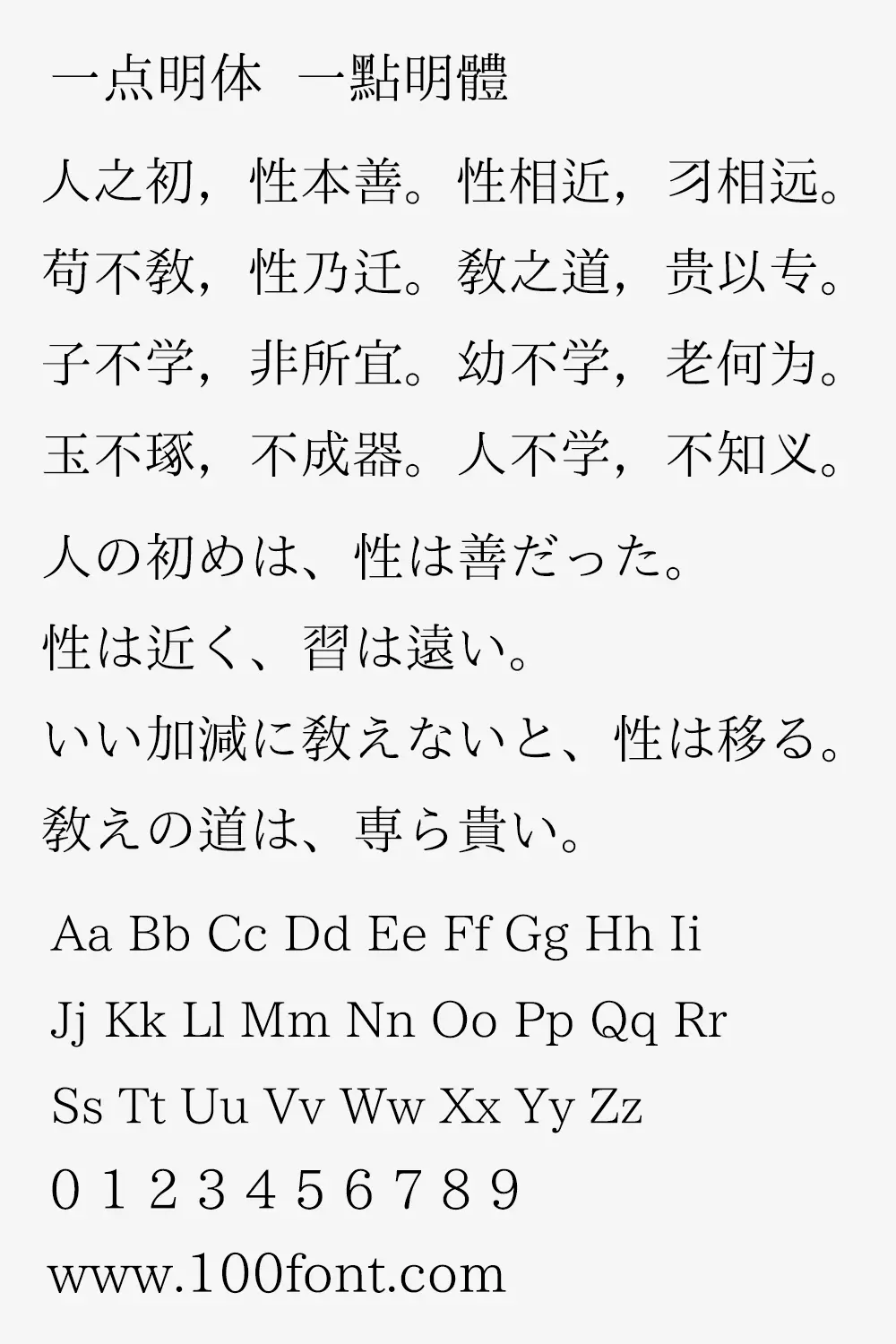
I.Ming ((I.明體 / 一點明體 / 一點明朝 / 一點明體 )乃系一套依照傳承字形標準化文件《傳承字形部件檢校表》的推薦字形標準,並以TrueType格式封裝、依照Unicode編碼的OpenType字體。
我們希望「I.明體」可以作為實際示範,讓大家明白製作字體時,可以採用依照傳承字形標準化文件推薦字形,同時仍然依照Unicode編碼、符合OpenType技術,並期待各字體廠商、字體制作者都能仿效,推出更多開源或商業市場上的傳承字形字體,以收拋磚引玉之效。
「I.明體」這字體名稱裡的「I」是羅馬數字「一」,「I.」唸作「一點([粵]Jat1 dim2、[中古]Qjit temx、[客]Jit7 diam3、[北]Yī diǎn、[日]いちてん、[英]One-dot)」,象徵筆畫的基本:點與線。
信念
漢字,在當今語文中,地位無可取代。它是唯一廣泛通行的意音文字(logogram),每個構字有其字理依據,可上追字源,追蹤每個漢字背後的故事。由龜甲獸骨、鐘鼎禮器上圖形味甚重的漢字,發展至今天,漢字展現了多變的外貌。
現在,進入了信息爆炸的社會,漢字仍不失其生命力。今天大家使用的漢字,主要有兩大類:一是手寫體,由前人的楷書、行書書法演變而來,講求靈活的變化,展示執筆者的修為,營造行間的氣韻;二是印刷體,亦活躍於各種電子屏幕,上宗中國蓬勃且領先全球的印刷術裡,所使用的雕版及活字造形,講求其清晰、理性,結構穩重而明目,筆畫井然且有理。
按類別不同,兩種字在筆畫表現上,一向有所差異。手寫求活,有些筆畫趨於書寫時的便易;印刷求精,筆畫大多保留傳統理性。因此,印刷體的傳承文字,本以致力保留字理為正道。
「I.明體」依照傳承字形標準化文件《傳承字形部件檢校表》的推薦字形標準制作,力求遵從字理,展現傳承漢字構字的科學系統。同時,我們另備「I.明體異體」,呈現傳統印版字中常見的異體。
「一點明體」(I.Ming):收錄力求遵從字理的傳承字形。
「一點明體CP」(I.MingCP):與「一點明體」一樣,唯全形標點置中。
「一點明體異體」(I.MingVar):部份漢字改為收錄一些也常見,但字理上未必比上者佔優的傳承字形。
「一點明體異體CP」(I.MingVarCP):與「一點明體異體」一樣,唯全形標點置中。
「新一細明體」(PMingI.U):與「一點明體CP」一樣,唯行高修改至跟Windows系統細明體相同。
「新一細明體異體」(PMingI.UVar):與「一點明體異體CP」一樣,唯行高修改至跟Windows系統細明體相同。
歷史
「I.明體」經過許多人的努力才誕生。其前身是「IPA字體」。
2009年,日本「IPA」以符合「開放原始碼促進會(Open Source Initiative)」開源定義的「IPA開放字體授權協議」,發佈兩款「IPA字體」,分別為「IPA明體(IPA明朝)」及「IPA黑體(IPAゴシック)」。字體衍生自林隆男(Takao Hayashi)所設計的兩款字形:TypeBank公司的「TB明體」和「TB黑體」。字體包含了日本常用的字元,以供日本人使用。
後來,經過多年的持續修補及修訂,「IPA明體」擴充成「IPAex明體」、「IPAmj明體」。在「IPAmj明體」裡,正體漢字部份已補完得頗齊全,只是仍有少數常用字缺字。預設顯示的寫法仍以日文為主,字體同時收錄了許多異體寫法,惟須採用特定程式方能顯示。其2013年11月的版本,收錄了CJK基本漢字18072個,擴展A漢字5765個,擴展B漢字25320個,擴展C漢字380個,擴展D漢字108個,未映像的異體等漢字9065個。
2013年底,Halasjack公開釋出「IPA明體補字」,在「IPAmj明體」的基礎上,修改了部份日文寫法為中文寫法,把異體字裡符合中文原體寫法,改為預設顯示的字元。他又用正體字替代缺少的簡體字。當中「一簡對多正」的字,如「發」、「歷」等,Halasjack增補了字元,不用某個正體字代替,以免出現別字。此外,Halasjack又自造了百餘個GB2312的缺字,使字體能夠完全顯示GB2312漢字,雖然部份簡體字顯示作正體字,但已能滿足大陸使用者的一般需要。字體並含有部份A區和B區漢字。
2014年年中,「I.字坊」(一點字坊)處理人內木一郎開始以「IPA明體補字」為基礎,增補、修改及整理字元,製作成「I.明體」,以應付正體(繁體)中文的需求。後來,幸得陳輝恆、李爾樅加入,大家一起傾力製作及修改字體檔案。同時,又得Extc、鍾啟堯、陳志泓、佟藍歌等仝寅提供各方面的支持,李擎宇、伍梓豪、鯤逰白圭、夜煞之樂、落霞孤鶩等協助製作簡化漢字,使「I.明體」字體日趨成熟。目前,「I.字坊」各仝寅已補完了所有Big5漢字、GB2312漢字、IICore漢字、《通用規範漢字表》漢字,以及《常用香港外字表》第1.8版中所有字元、「再會豆腐字」《本土語言外字表》2020年版所有字元、《康熙字典》所有字頭,此外還製作了部首及補充部首、筆畫、注音符號及注音符號擴展、蘇州碼子、麻雀牌、中國象棋、中國算籌、中式「正」字計數符號、八卦、易經六十四卦、太玄經八十一卦等字符,覆蓋絕大部份正體(繁體)中文文本所使用的字元,滿足香港和臺灣使用者的一般需求。「I.字坊」仝寅亦進一步修改漢字寫法,依據傳承字形標準化文件,以傳承下來的原體寫法(一般來說,日本地區通稱「康熙字典體」,大陸地區俗稱「舊字形」)為依歸。這種寫法最能保留漢字字理,亦符合正體地區人士多年的閱讀習慣,更能使字元設計得較美觀。
字體文件帶CP的意思:字體名字中帶有CP表示標點符號居中,其他方面和其他字體一樣。